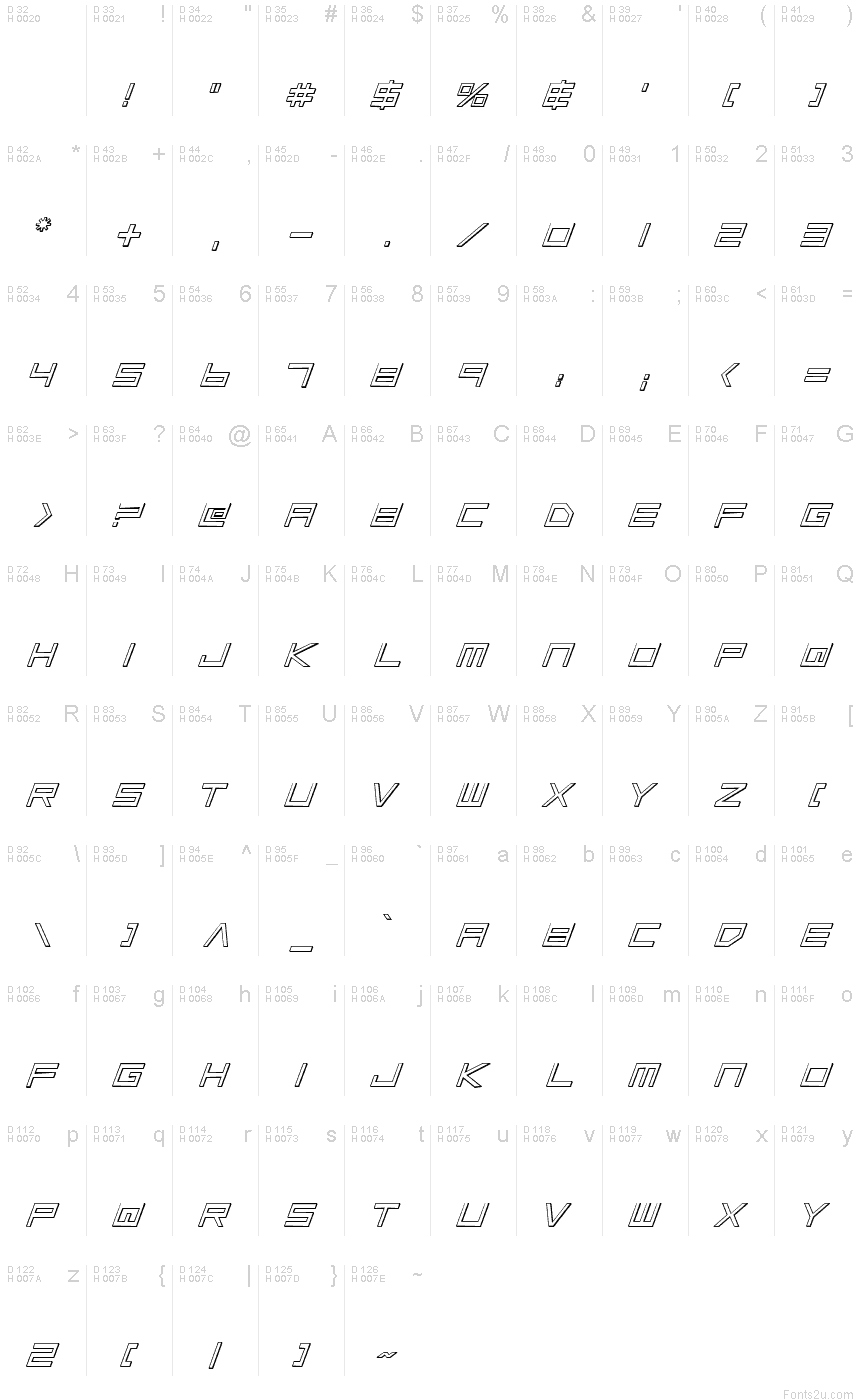
Low Gun Screen Outline Italic di Iconian Fonts è un font display gratuito in stile techno con contorno e un'inclinazione rapida che ricorda gli schermi dei videogiochi. Le lettere sono fortemente inclinate verso destra, costruite con tratti geometrici ampi e angoli tagliati che conferiscono alle maiuscole un aspetto slanciato, quasi corazzato, piuttosto che neutro.
Si adatta perfettamente a poster di fantascienza, branding arcade, grafiche per e-sport, titoli e copertine in cui un font gratuito può donare dinamismo senza risultare caotico. Dato che il contorno rimane aperto e le forme sono ampie ed enfatiche, funziona egregiamente anche per titoli brevi, logotipi e monogrammi che richiedono un'attitudine meccanica e orientata al futuro.